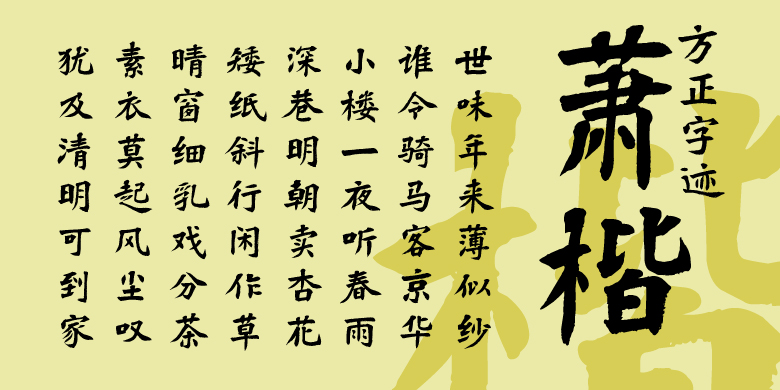
方正字迹-萧楷
肖华
楷书、魏碑、常规书写·毛笔
萧楷以魏碑楷书的雄强、厚重、洒脱、率真、浪漫为根,融入南帖的温润、典雅、妍美,使碑骨帖韵神而化之,形成了萧楷雍容雄浑、典雅庄重、洒脱奔放的庙堂新境界,焕发出中华文化五千年传承泱泱正大气象。萧楷为公共场所、风景名胜、寺观殿宇,广告牌匾、庄重活动用字和书法临摹学习提供了新的选择。
萧楷作者三十多年一直从事魏碑楷书的研究和创作,成绩斐然。是北京大学书法艺术研究所二十年来的授课专家。清华大学出版社三年内出版了作者9本书法专著,并获得清华大学出版社“最美实用书法教材”荣誉称号。受邀为北京市政协新落成的常委会议大厅书写一米五高,十五米宽的巨幅魏碑楷书《兰亭序》。